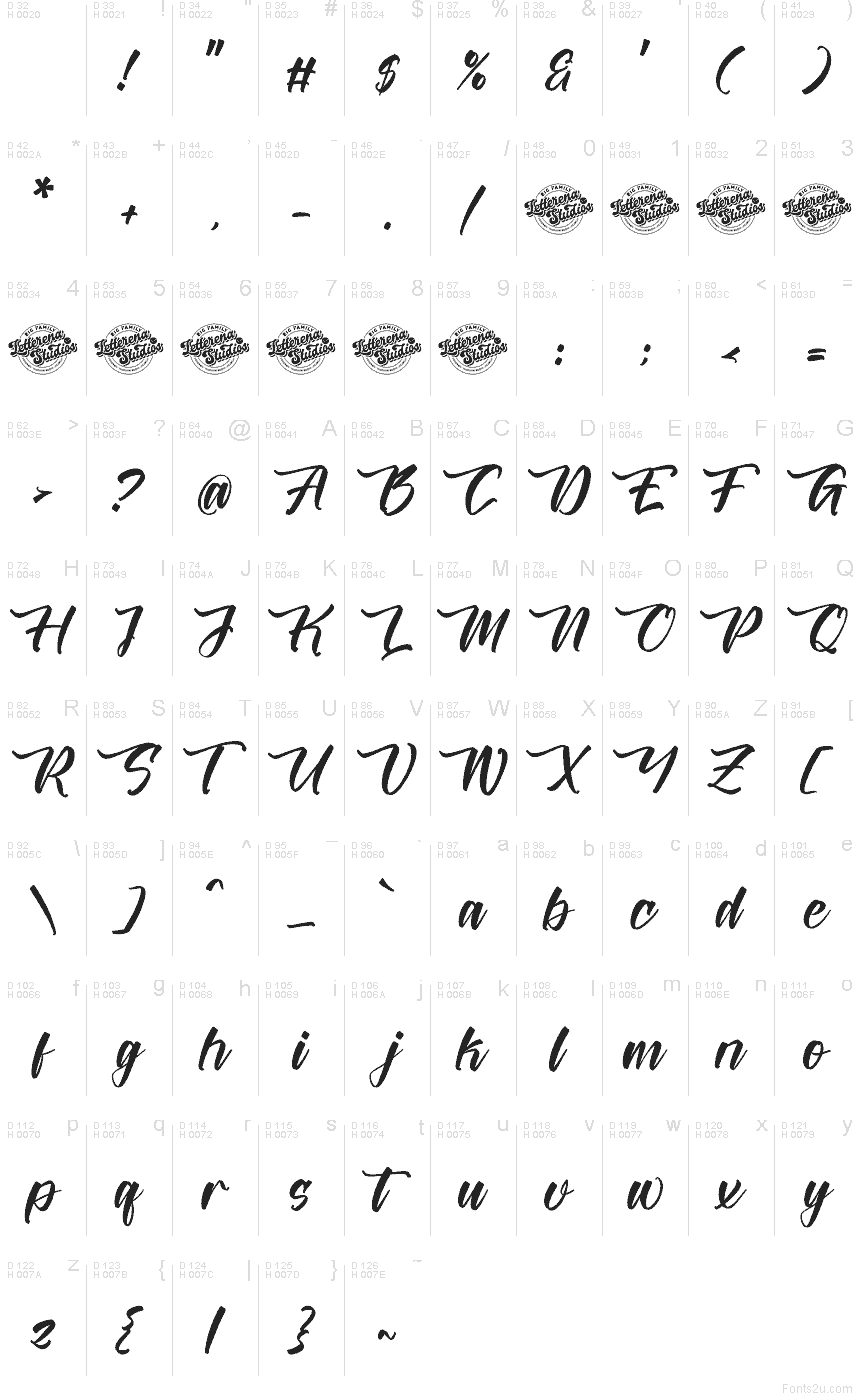
Battrich Delighta, de Letterena Studios, es una tipografía gratuita de caligrafía a pincel con un ritmo rápido, gestual y una actitud desenfadada de script de moda. Sus letras destacan por trazos gruesos que se afilan y largas entradas fluidas, mientras que su alto contraste y sus giros rápidos la mantienen viva y natural, lejos de lo convencional.
Es ideal para branding, packaging de boutiques, editoriales de belleza, citas en redes sociales y papelería de eventos, donde una fuente necesita más personalidad que perfección. Úsala para titulares cortos, portadas o tarjetas de título, especialmente cuando esas largas florituras puedan tomar el protagonismo y hacer que unas pocas palabras se sientan elegantes y sofisticadas.